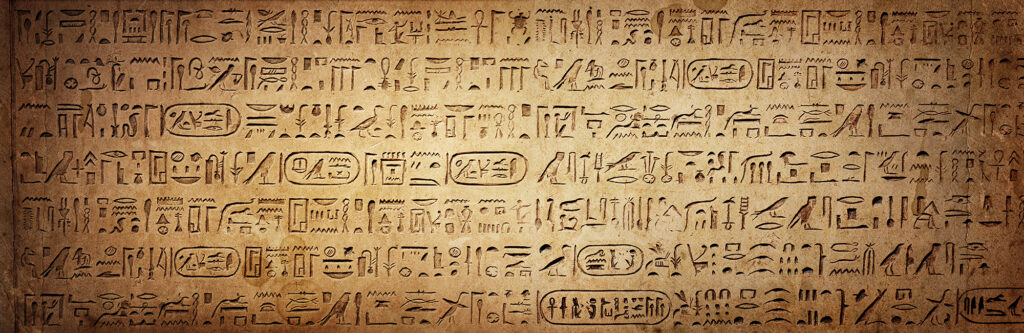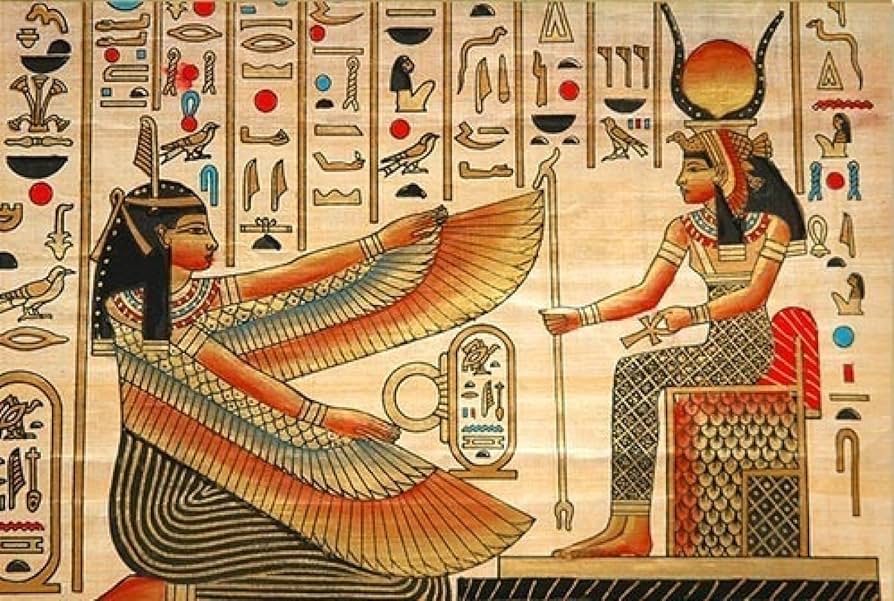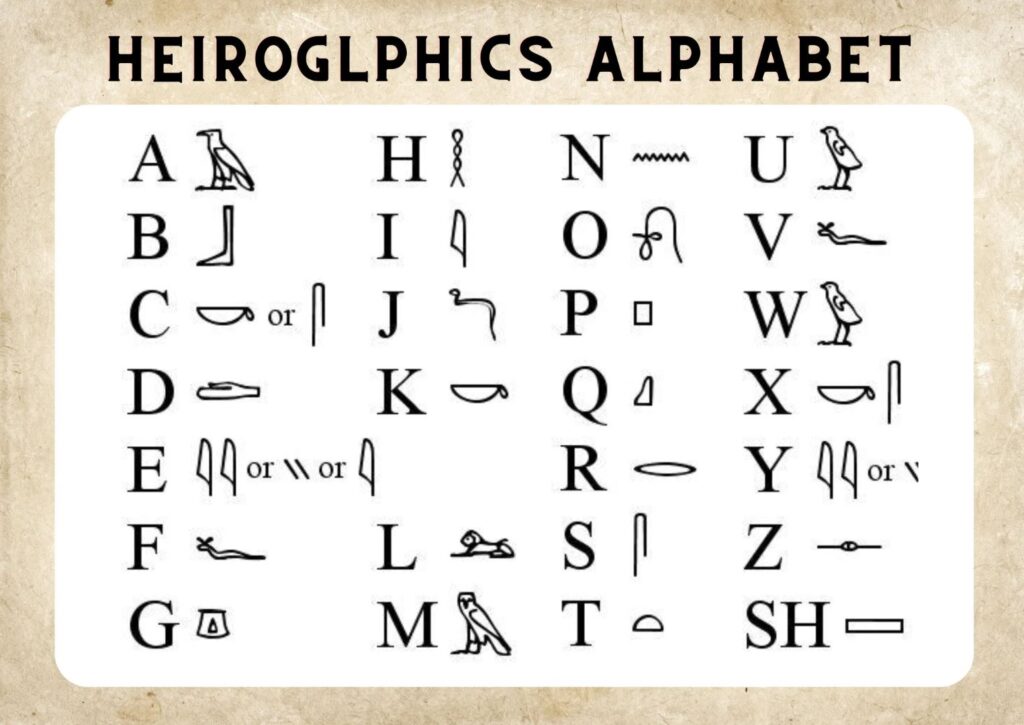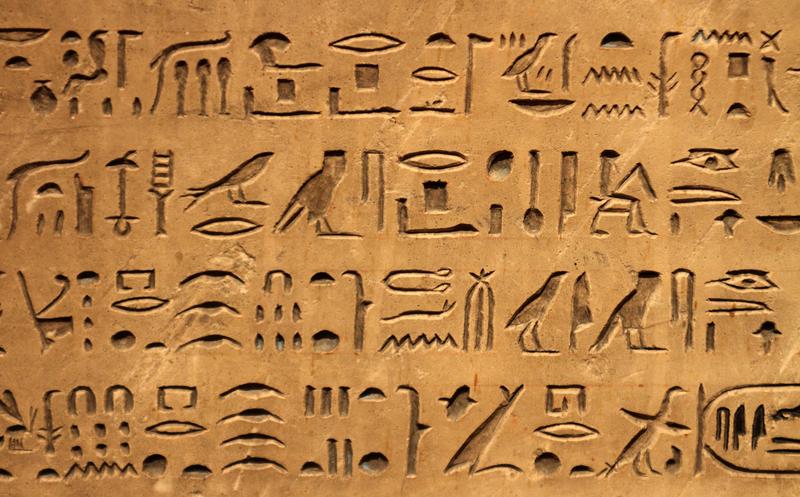
2500 – 3000 v. Chr.
Im Niltal entstehen die ägyptischen Hieroglyphen – ein komplexes Schriftsystem aus Bild- und Lautzeichen, mit dem erstaunlich präzise Inhalte vermittelt werden konnten. Diese Schriftform gilt als hohe Kunst der Gestaltung, war jedoch äußerst aufwendig und daher für den Alltag kaum praktikabel. Durch Fremdeinflüsse, Weiterentwicklungen und das Bedürfnis nach einfacheren Schriftsystemen verlor sie allmählich an Bedeutung.
Heute schreibt niemand mehr Aufsätze in Keilschrift oder Fachartikel in Hieroglyphen, doch Piktogramme und Ideogramme sind allgegenwärtig. Man begegnet ihnen im Straßenverkehr, in Gebrauchsanleitungen, in der Kartografie, auf Wasch- und Bügeletiketten und besonders im Internet. Ihr Vorteil liegt auf der Hand: Sie verdichten Informationen auf kleinstem Raum und ermöglichen unmittelbares Erfassen mit einem Blick. Gerade in Regionen mit hohem Analphabetismus erleichtert der Einsatz solcher Zeichen das Leben in vielerlei Hinsicht.